在线简繁转换器,无需注册,文本简体繁体快速转换
做文案、跨境运营、古籍制作的从业者们,几乎每天都能遇到文字简繁转换的工作内容,尤其是面向港澳台客户的时候,商务合作需要将大部分文字需要转换成繁体才能用,开设品牌也得制作一个繁体字的 LOGO 才适合。市面上大多数字体转换工具要么全是弹窗广告,要么强制注册登录,还经常出现转换不准确的现象,严重拖慢工作效率。而今天要给大家介绍的工具——字由,完美解决了上述这些令人头疼的问题,不仅可以在线简繁转换,还提供了大量适配多种场景的繁体字资源,绝对是设计界的高效率字体神器。接下来,我将从简繁转换流程、简繁转换器的优势以及热门繁体字资源推荐三个方面来介绍,保证新手小白也能一秒学会。
一、在线简繁转换的流程
1.输入文字在线转换繁体效果
- 进入字体资源页面
搜索“字由”并点击进入官网,在首页顶部导航栏点击“全部字体”。
- 挑选心仪的字体资源
永科可以直接在搜索框输入“繁”,下方页面会弹出字由内的所有繁体字模板;或者在筛选功能处的“字体语言”里选择“繁体中文”,在这些字体资源中,点击选择一款你想要转换的繁体字。
- 输入文字完成转换
进入字体详情页面后,在文本框内输入你的文案,就能立刻转换为当前繁体的效果。
2.客户端实现在 PS、Sketch 中的繁体一键转换
- 搜索繁体字资源
用户注册登录字由客户端之后,在搜索框内输入“繁”,在众多繁体字中选择一个你最喜欢的字体。
- 一键激活完成转换
在 PS 等设计软件中,选中需要转换的文字,回到字由客户端,点击心仪的繁体字体,点击右侧“激活”按钮,即可完成字体应用。
二、在线简繁转换器的优势功能
相较于市面上的大部分字体转换工具,字由是一个集字体应用、管理、授权服务于一体的全能型字体管理工具,操作零门槛,无需设计经验,并提供 AI 一键生成同款字体,AI 识字、字体特效等实用功能,目前注册用户远超 2000万。那么,字由到底有哪些核心优势呢?
1.一键应用字体,效率极高
以往的字体使用流程是:找字体、下载字体、解压字体包再安装字体,而字由完全优化了这套流程,为设计师提供了更多便利。通过字由客户端可实现在 PS、AI、ID、XD、Figma、Sketch、CDR 等设计软件中一键应用字体,无需下载安装字体包,即可完成字体应用,省去了字体查找、下载、安装的麻烦。
3.AI 识字功能,寻找繁体字无压力
字由的 AI 识字是一个特色功能,基于海量字体数据,通过 OCR 和自研大模型智能分析,用户只需上传图片,即可智能识别图片中所用字体及其授权类型,让设计师找字省心,设计安心。这也就是说,如果工作中客户给你发来了一张繁体字图片,要求你按照这种风格来转换文字,在你不知道繁体字名称的情况下,就可以上传到字由,让它来识别。
三、热门繁体字资源推荐
了解了转换流程和特色功能,挑选篆体字资源也是很重要的一环。不同风格的字体资源呈现的效果不同,为了便于大家选择,我来推荐几款使用率较高的繁体字,供大家参考。
1.汉仪行楷繁
汉仪行楷繁是一款介于行书的活泼与楷书的端正之间的书法体,自带毛笔手写质感,呈现出浓浓的古典书卷气息。造型秀美适意,字形端庄优雅,笔画流畅,点画呼应,舒缓自如,读来如行云流水,一气呵成,具有较强的动势美感。
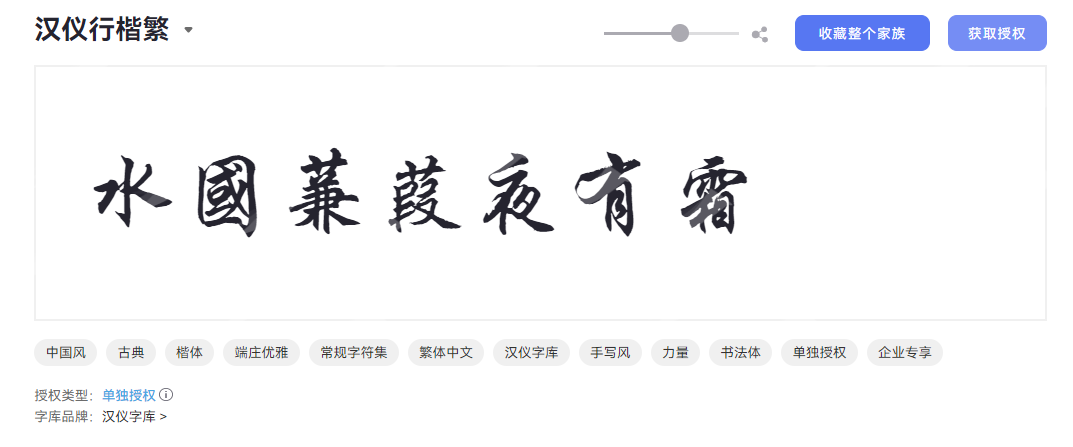
2.汉仪星宇体繁
汉仪星宇体繁是一款力量感十足的繁体手写书法字体,保留了开题本身的特性,又添加了绘画感的线条,整体风格更加洒脱大气,雄浑开阔。笔画粗细对比鲜明,锋利处更锋芒,婉转处更婉约,笔触富有张力。
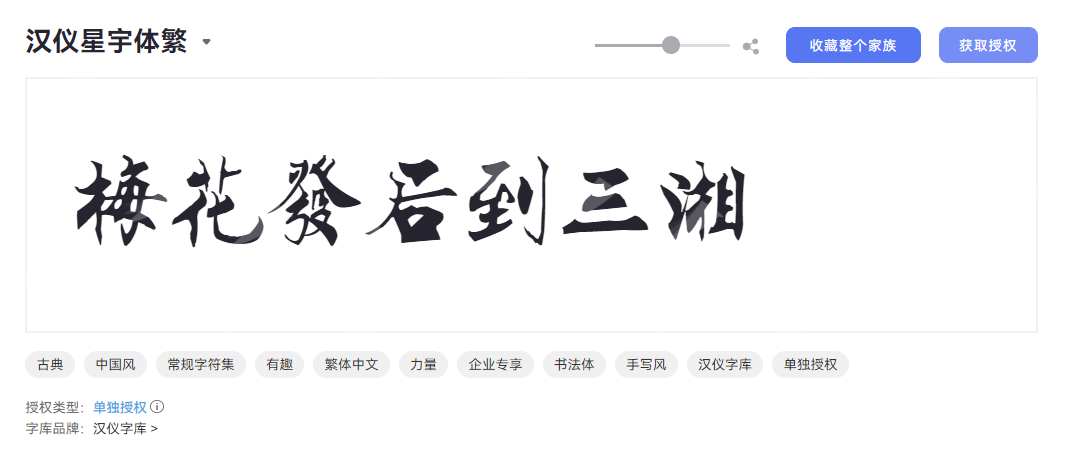
3.汉仪雪君体繁
汉仪雪君体繁是汉仪字库推出的一款极具东方古典韵味又不失现代审美情趣的精品字体,象征着纯净、端庄、高洁、雅致的特点。它将传统书法的精髓与现代设计的简洁流畅完美融合,形成了独树一帜的风格,致力于在数字化时代,以一种优雅而富有格调的方式,呈现中文汉字的独特魅力。
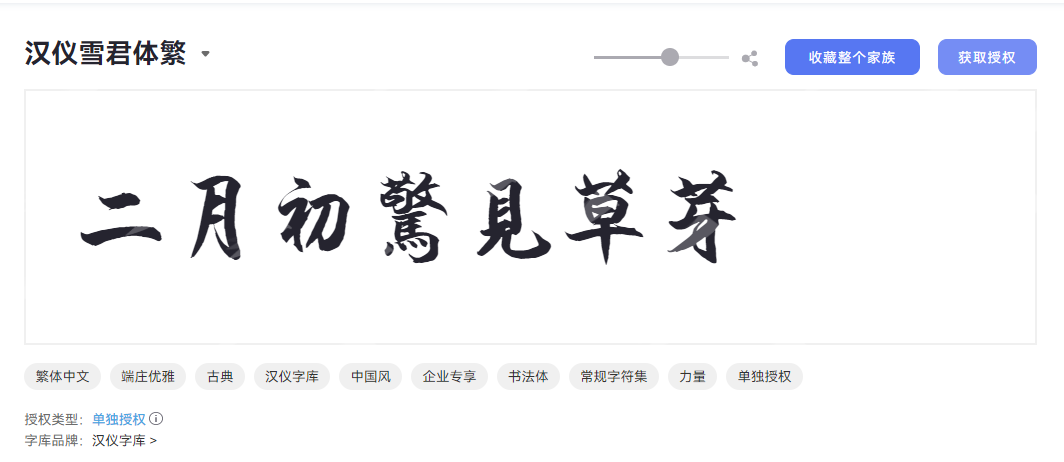
综上所述,想要快速完成简体繁体的转换,字由是最优选择。区别于市面上功能单一、限制繁多、广告众多的第三方字体转换器,字由的转换流程简单高效、字体版权有保障、授权方式灵活,还有 AI 识字功能帮你快速识别字体,可谓是广大设计师的“绝佳帮手”!不管是处理繁体字文件资料、编辑面向港台客户的文案,还是需要整理制作古籍文字、设计繁体字 Logo,你都可以依靠字由来完成简繁转换。感兴趣的小伙伴们亲自去体验一下吧!